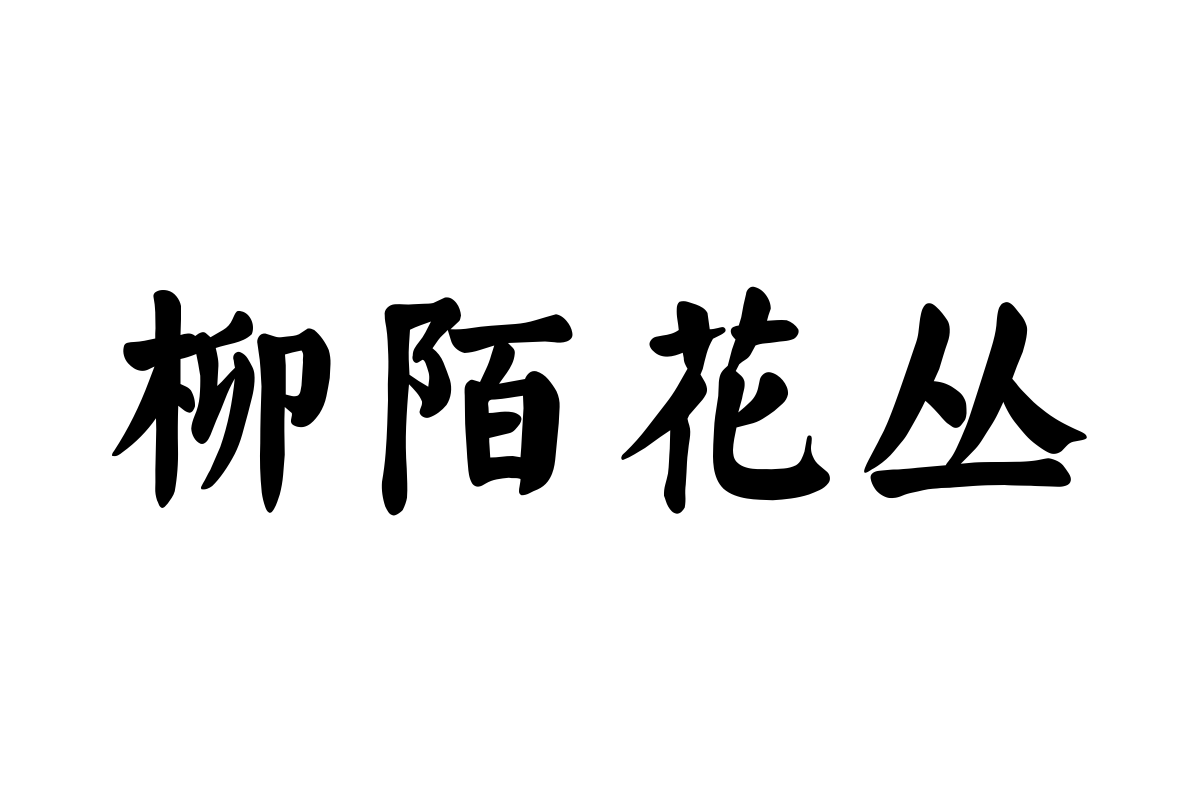
汉仪颜楷字体是一款具有独特韵味和艺术感的字体,其设计灵感来源于中国的传统书法艺术。这款字体的特点在于其笔画流畅、结构严谨,既有颜体楷书的古朴典雅,又不失现代审美的简洁大方。
汉仪颜楷字体适用于各种需要书写中文的场合,如书籍、报纸、杂志、广告、商标等。它的使用不仅能够提升文字的美感,还能够增强信息的传达效果,使读者更容易理解和接受所传递的信息。
总的来说,汉仪颜楷字体是一款非常优秀的中文字体,无论是在传统书法领域还是在现代设计中,都得到了广泛的应用和认可。